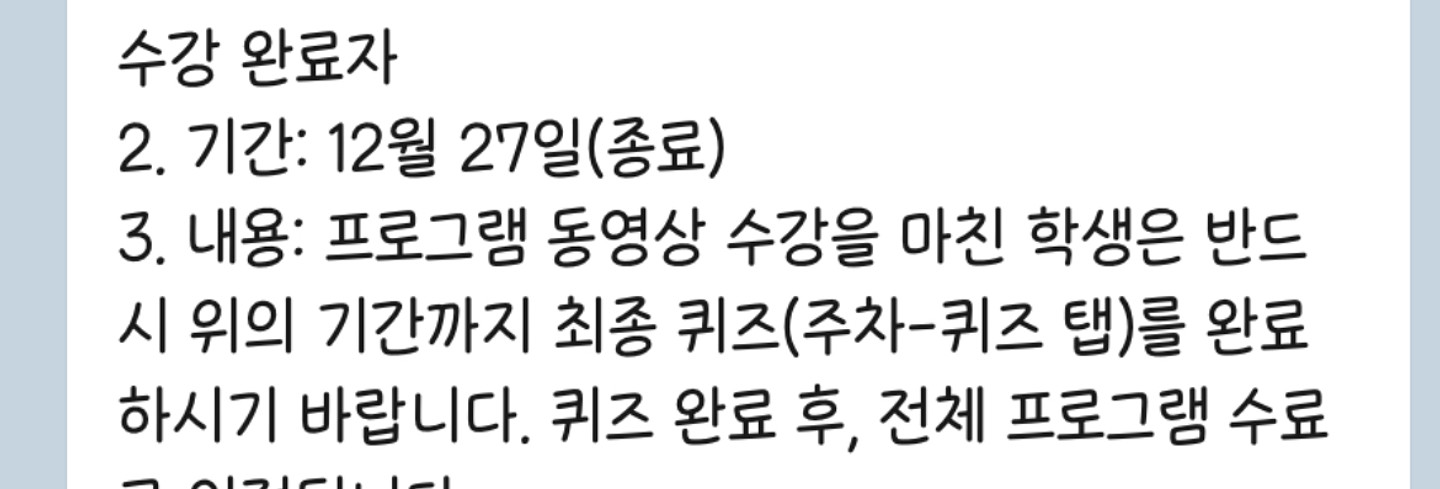
우선 세월호 희생자들의 명복을 빕니다! "그날의 슬픔을 잊지 않고, 더 안전한 대한민국으로" 여기에 사용된 폰트가 무엇인지 궁금하네요!
https://www.instagram.com/p/DXGywkVkkX5/?img_index=4&igsh=MXB1aW51ZDg4a2NodA== 출처입니다 너무 궁금해요
무슨 폰트인지 알 수 있을까요 https://x.com/canele0101/status/2044350356503871951?s=46&t=HRc96GbgQHLKXCyJgvI1Ew 트윗 내 사진에 쓰인 폰트입니다 ㅠ
카톡 폰트를 변경했는데 기존 폰트가 뭐였는지 모르겠어요 몇가지 후보군이었던 여기어때, 프리텐다드, 나눔스퀘어는 다 ㅠ 모양이 다르더라구요 (찾는폰트는 ㅠ 모양의 왼쪽획이 휘어있으나 후보군 폰트들은 일자임) 제발 찾아주세요ㅠㅠ
영문폰트 정보가 궁금합니다! 이탤릭체와 일반체가 섞여짜인 것 같은데, 딱 저 모양의 이탤릭체는 아무리 찾아도 같은게 없네요,, h k w e y p 등 특징이 많은데 아무리 찾아도 없어요ㅠㅠ